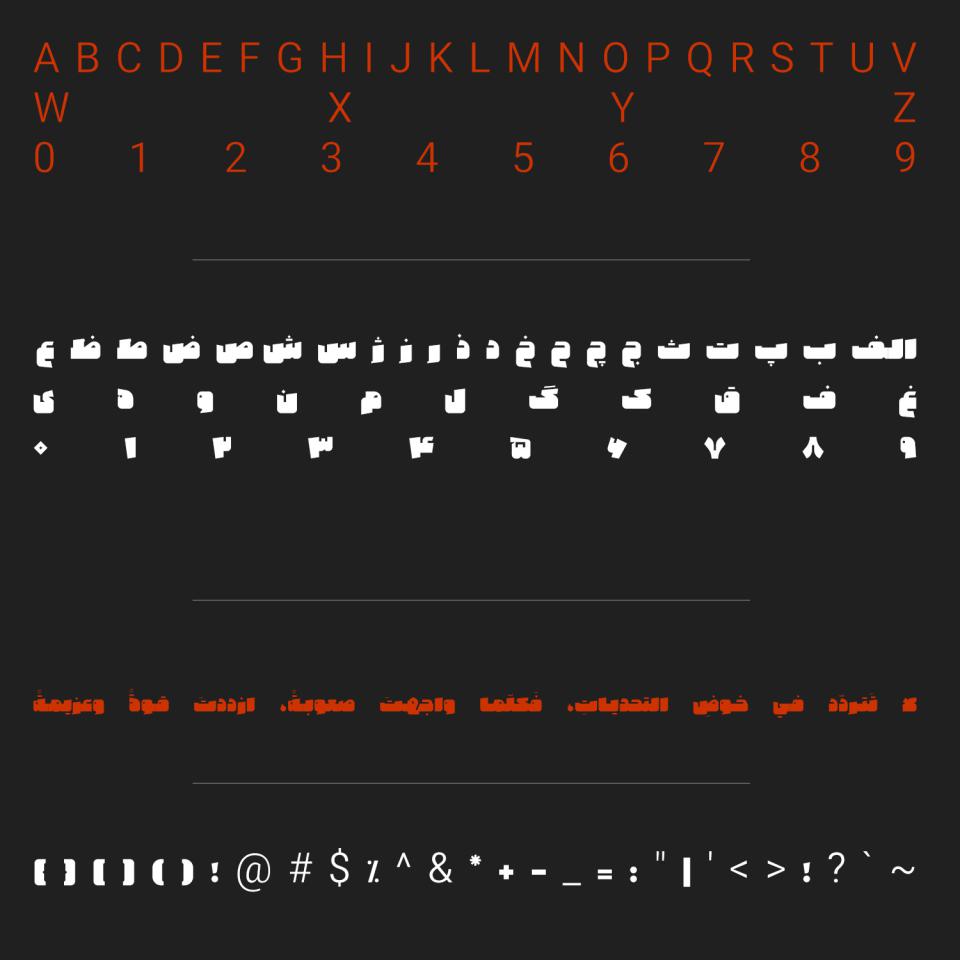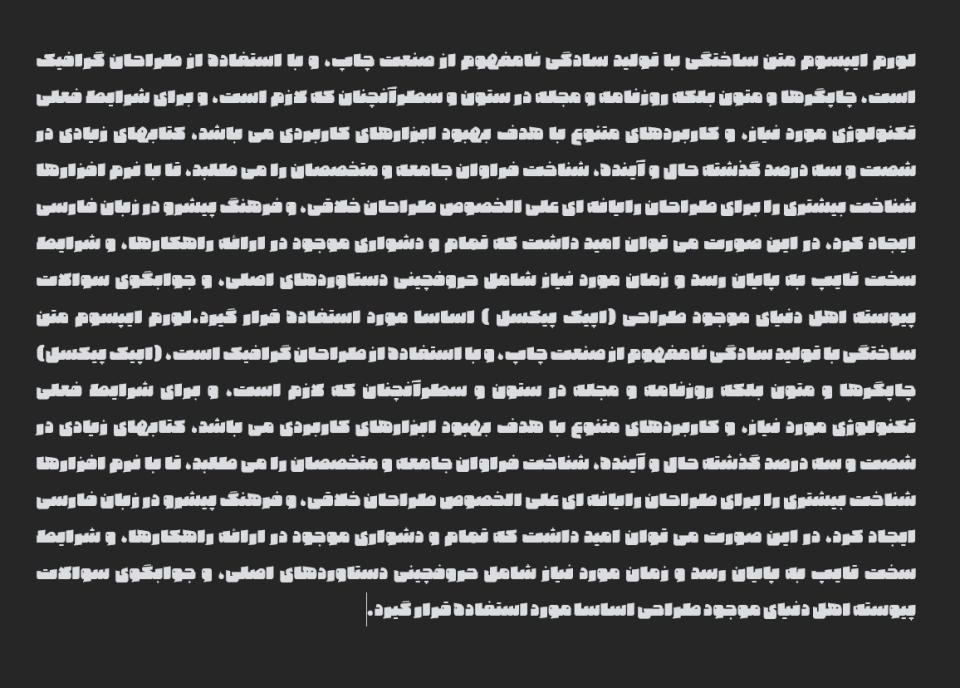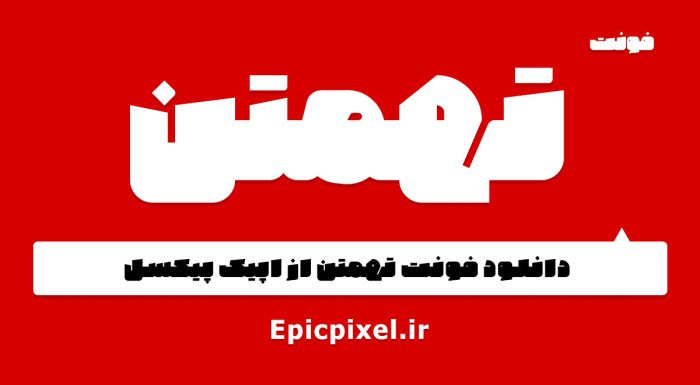
فونت تهمتن، یک انتخاب جسورانه برای طراحانی است که به دنبال جلوه ای قدرتمند و متمایز در آثار خود هستند. این فونت با ساختار هندسی و وزن بسیار سنگین خود، حسی از استحکام و اقتدار را به مخاطب القا می کند و برای عناوین، پوسترهای تبلیغاتی و جلد کتاب ها که نیاز به دیده شدن و تأثیرگذاری فوری دارند، گزینه ای ایده آل است.
یکی از ویژگی های برجسته تهمتن، ضخامت بی نظیر حروف آن است که در تایپوگرافی فارسی کمتر دیده می شود. این ویژگی، نوشته ها را به شدت نمایان و چشمگیر می کند و به آن ها ابهت خاصی می بخشد. فرض کنید می خواهید عنوانی برای یک رویداد مهم یا یک محصول خاص طراحی کنید؛ تهمتن با حضور قاطع خود، پیام شما را به گونه ای منتقل می کند که در ذهن مخاطب حک شود.
با وجود این مزایا، باید به این نکته هم توجه داشت که استفاده از تهمتن در متون طولانی یا با اندازه کوچک، به دلیل فشردگی و وزن زیاد حروف، می تواند خوانایی را کاهش دهد. بنابراین، بهترین کاربرد آن در فضاهایی است که نیاز به تأثیر بصری قوی در کوتاه ترین زمان ممکن وجود دارد. در واقع، تهمتن یک فونت برای خودنمایی است، نه برای ظرافت.
اگر به دنبال فونتی هستید که در نگاه اول، قدرت و جسارت را به نمایش بگذارد و می خواهید نوشته هایتان در میان انبوهی از طرح ها، برجسته و منحصربه فرد باشند، تهمتن همان چیزی است که به آن نیاز دارید. این فونت، با وجود محدودیت های خود در استفاده های طولانی، در جایگاه مناسب، اثری ماندگار و بی نظیر خلق می کند.